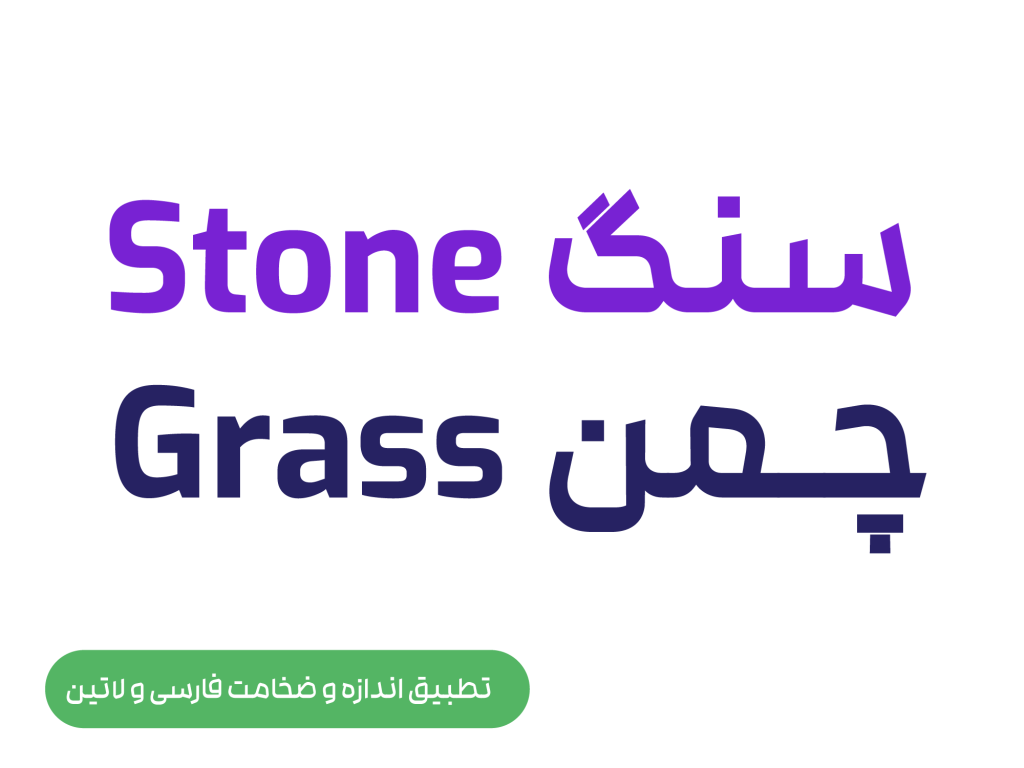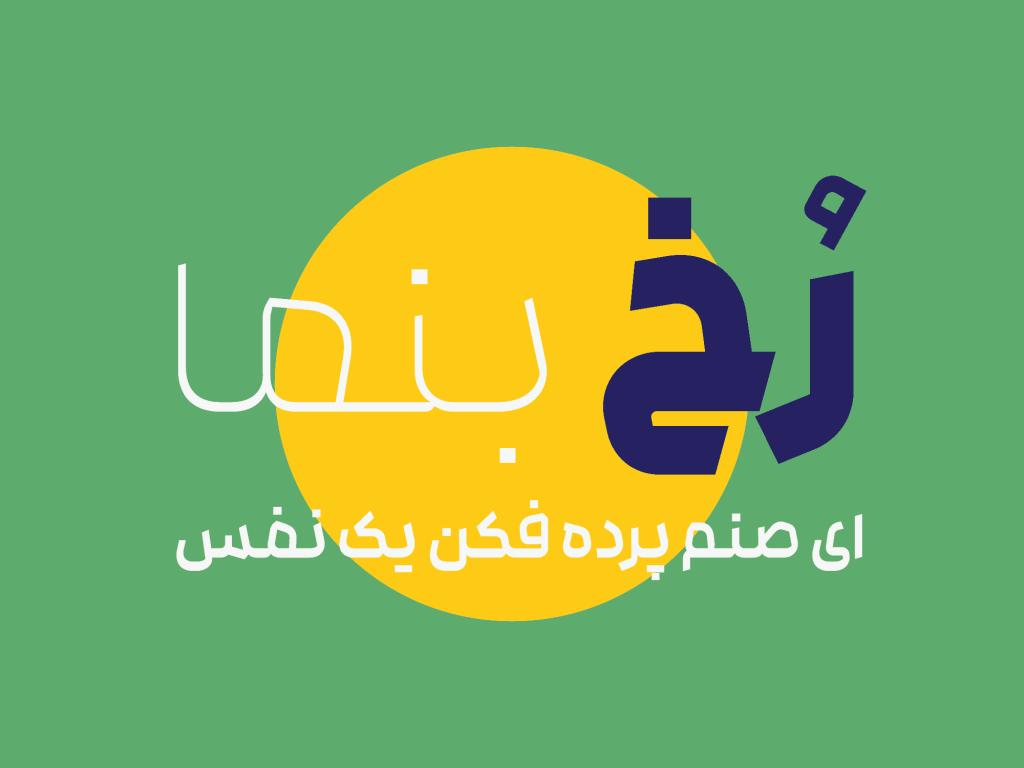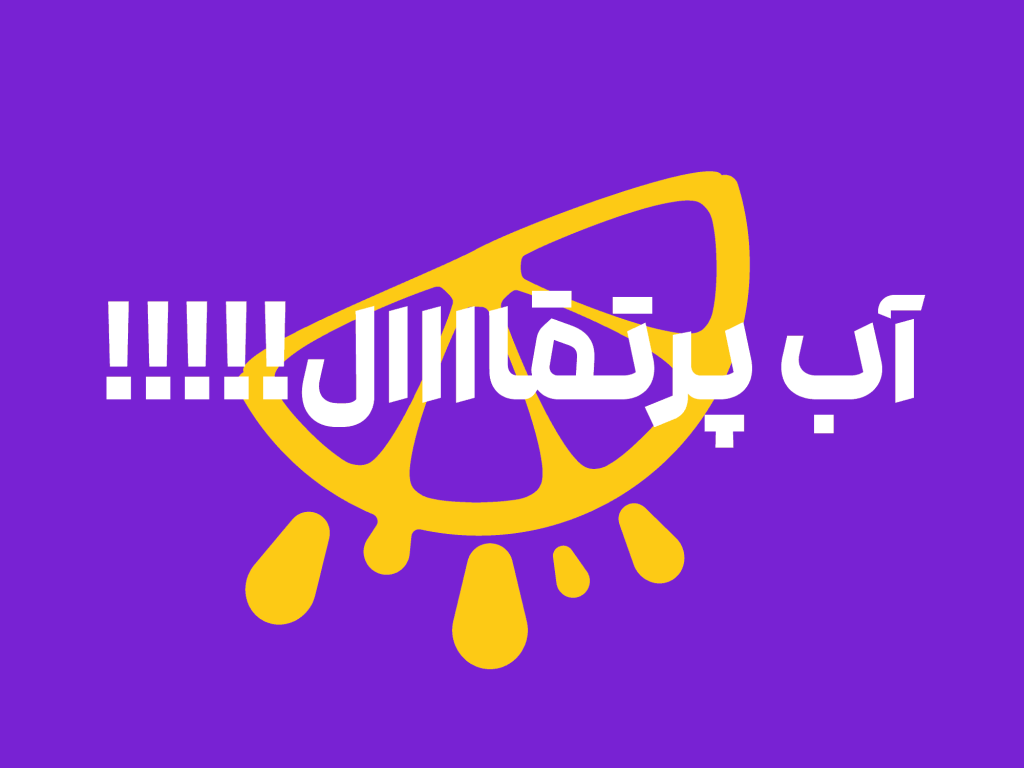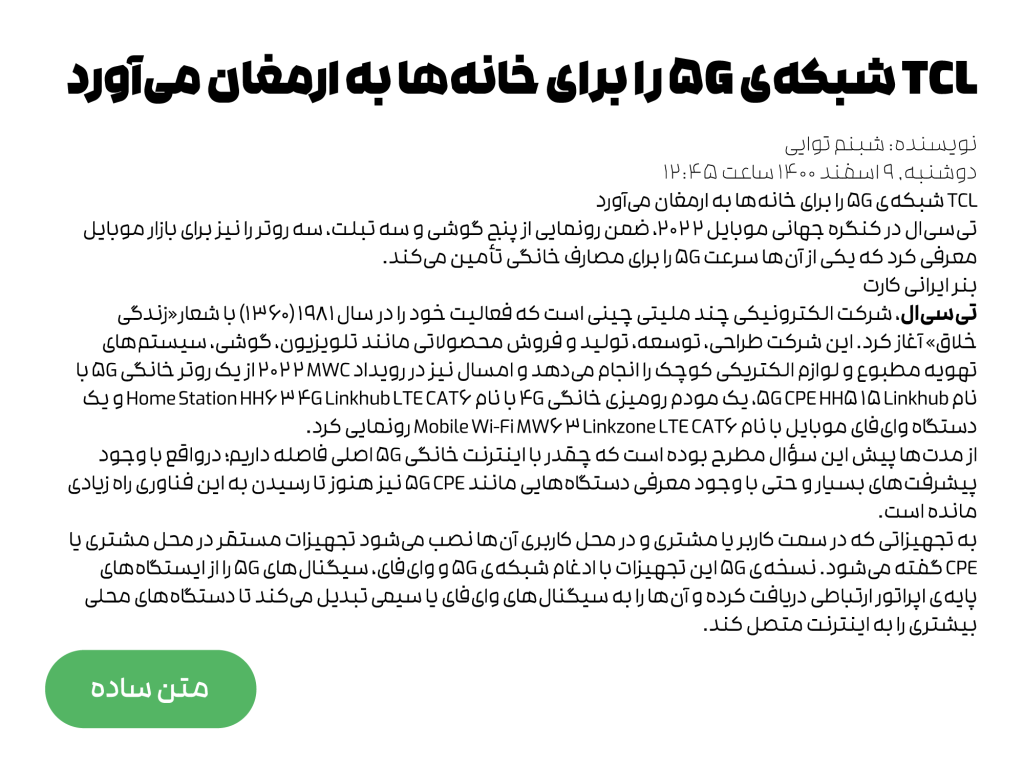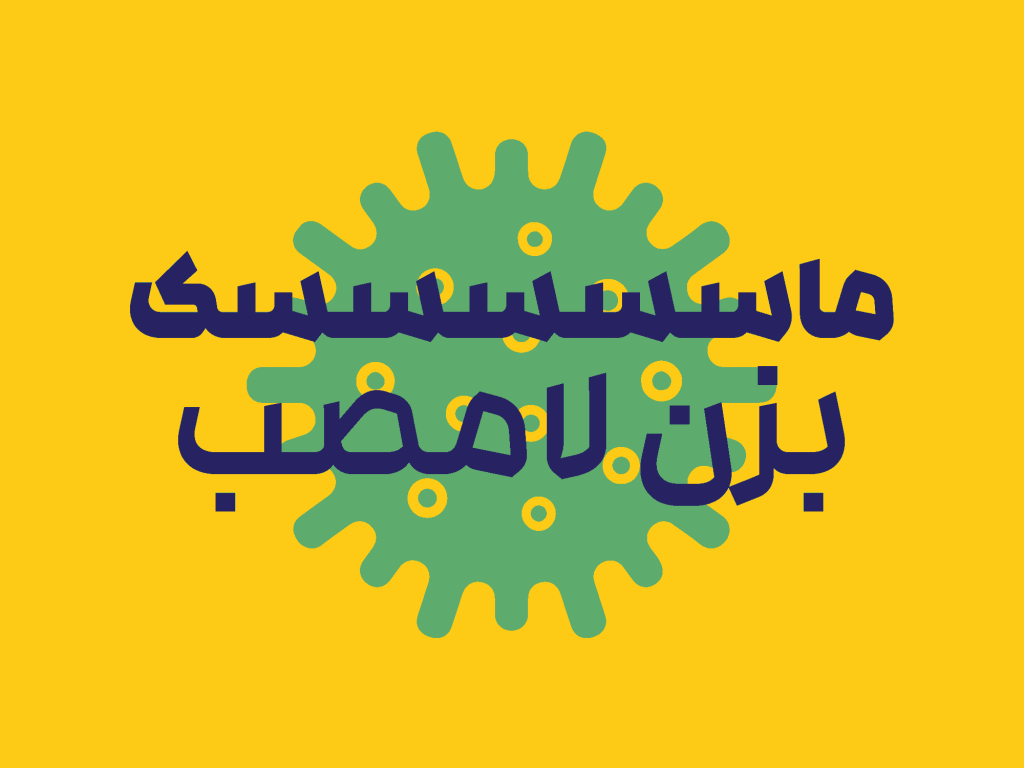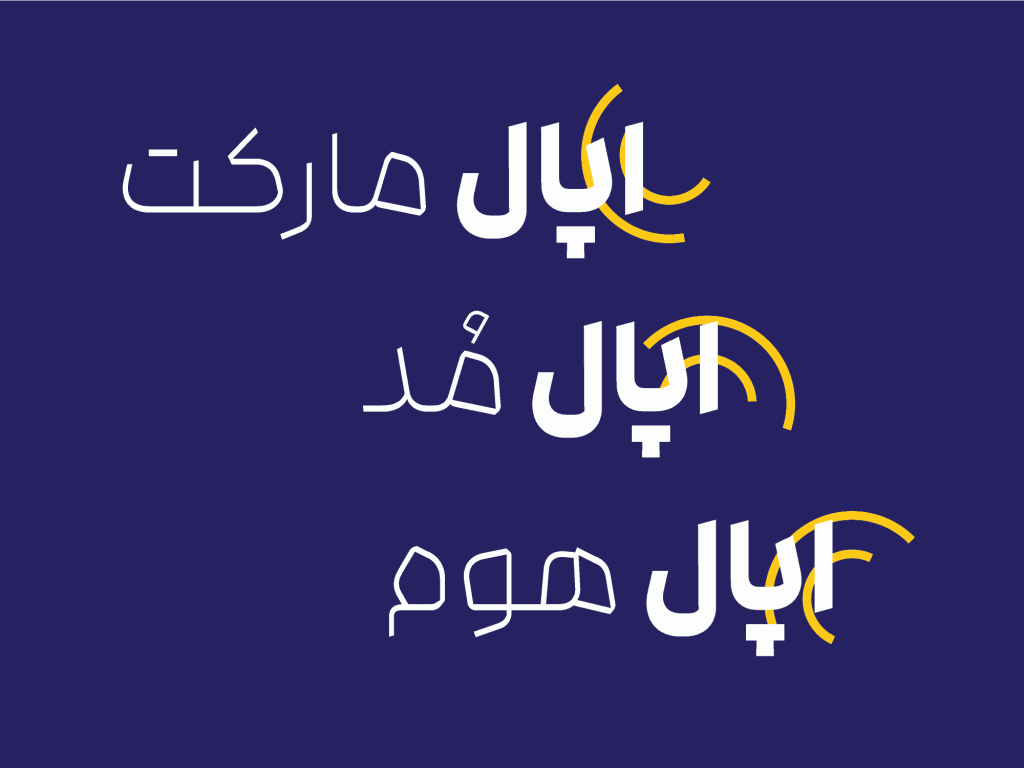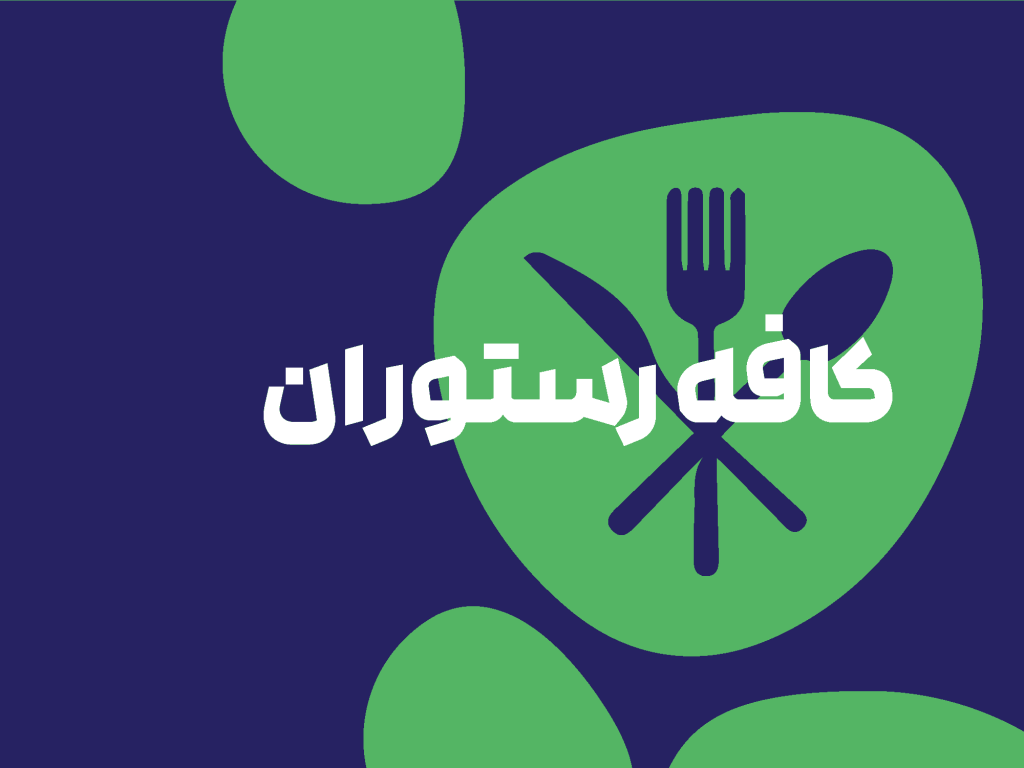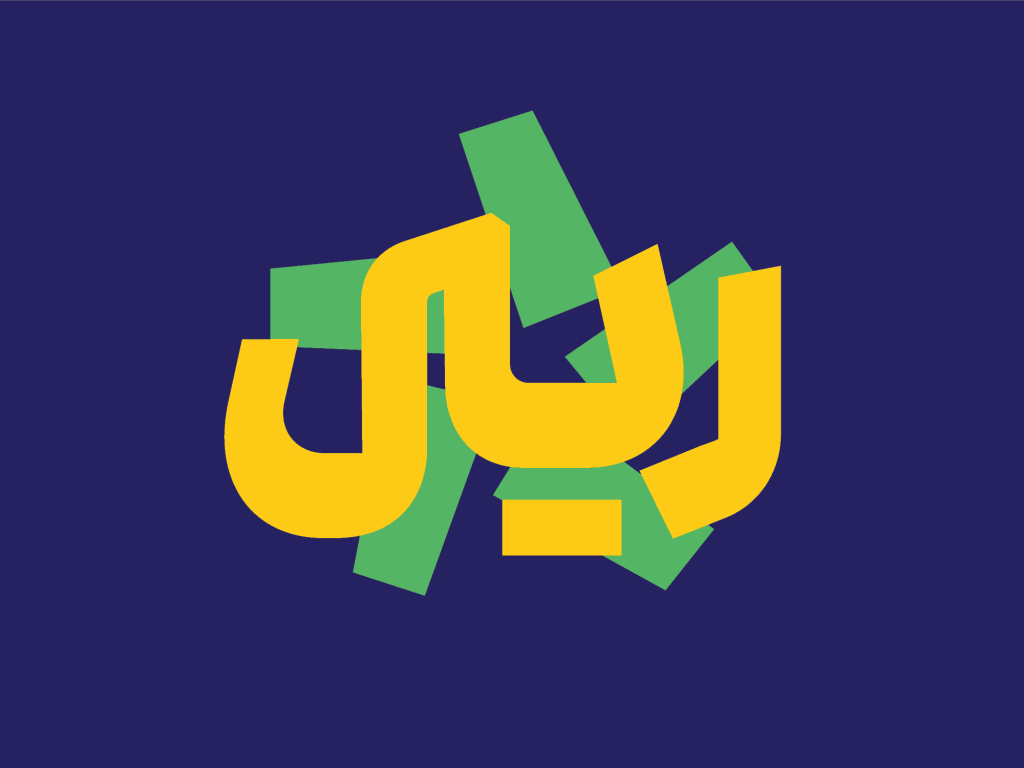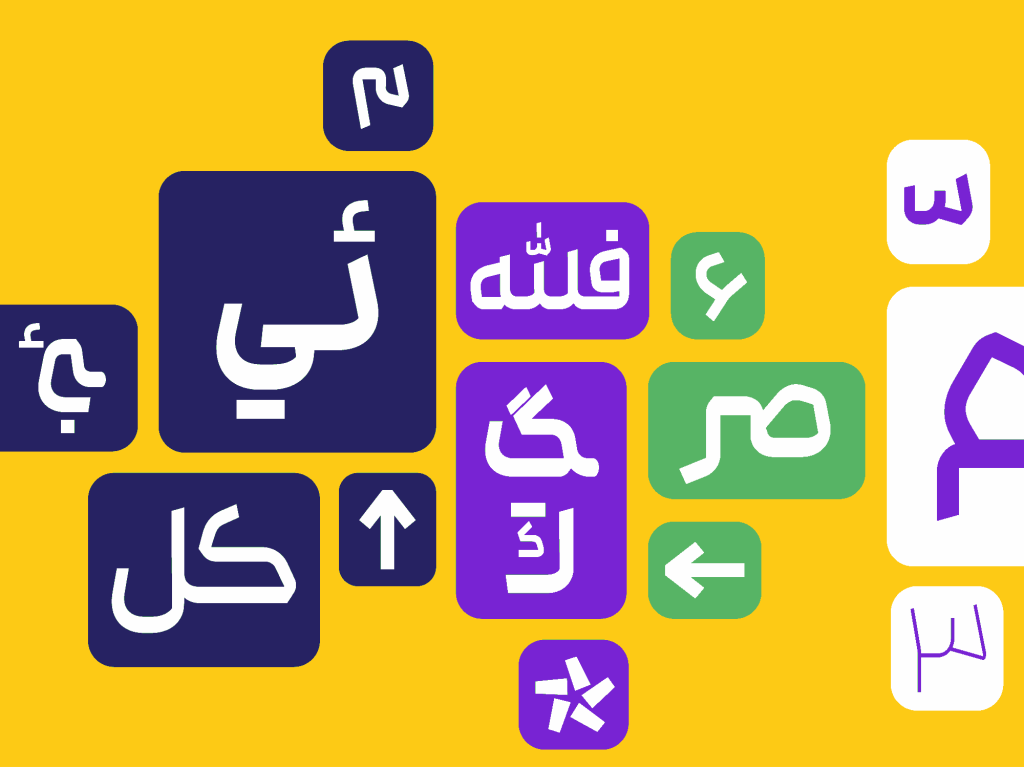
فونت رخ – جذب نگاه مخاطبان
فونت رخ توسط کامیاب جعفری طراحی گردیده است. این قلم مناسب عناوین و تیتر های خاص و تبلیغاتی است. ویژگی نمایشی رخ سبب جذب نگاه بینندگان و خوانندگان به خود است. به عبارت ساده تر می توان گفت این قلم همانند نامش به گونه ای طراحی گشته تا رخ نمایی کند و چشم ها را به خود تسخیر نماید.
البته درجه نمایشی بودن بالا در رخ ذره ای از میزان خوانایی آن کم نکرده و حتی بر ویژگی مذکور افزوده است. از این قلم به دلیل ویژگی نمایشی و منحصر به فرد بودن ظاهر آن می توان در طراحی لوگو تایپ نیز استفاده نمود. به عبارت ساده تر طراحیِ خاص و ویژه حروف در این فونت باعث میشود تا هر نوشتهای با صورتی جدید و نو ظاهر شود.
در این قلم حروف بالا رونده دارای حداقل کنتراست هستند به عبارت دیگر چشمها و دندانههای بلند در کنار الفهای کوتاه قرار گرفته اند. تمرکز عمده طراح بر شکل گیری منحصر به فرد حروف و گلیف های این قلم بوده است.
فونت رخ و پشتبانی از حروف جایگزین و حالت متغییر
رخ همه نیاز های مشتریان را مرتفع می کند . این تایپ فیس زیبا دارای نسخه وریبل یا متغییر می باشد (که سبب افزایش سرعت لود صفحات و کاهش حجم فایل های نصبی است). هم چنین این قلم خاص و منحصر به فرد از حروف و عبارت های جاگزین نیز پشتیبانی می کند.
زبان های فارسی، عربی، کوردی، اردو و انگلیسی را پشتیبانی می کند . در زیر می توانید تصاویر نمونه از این قلم زیبا را مشاهده کنید.